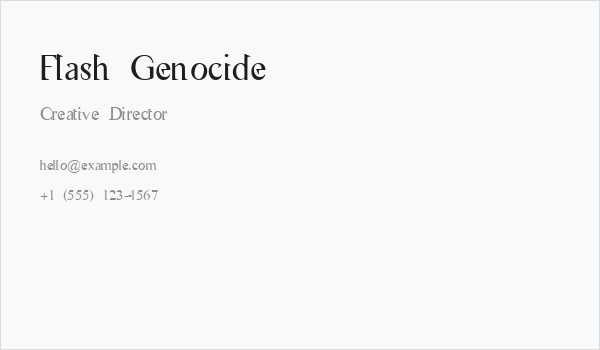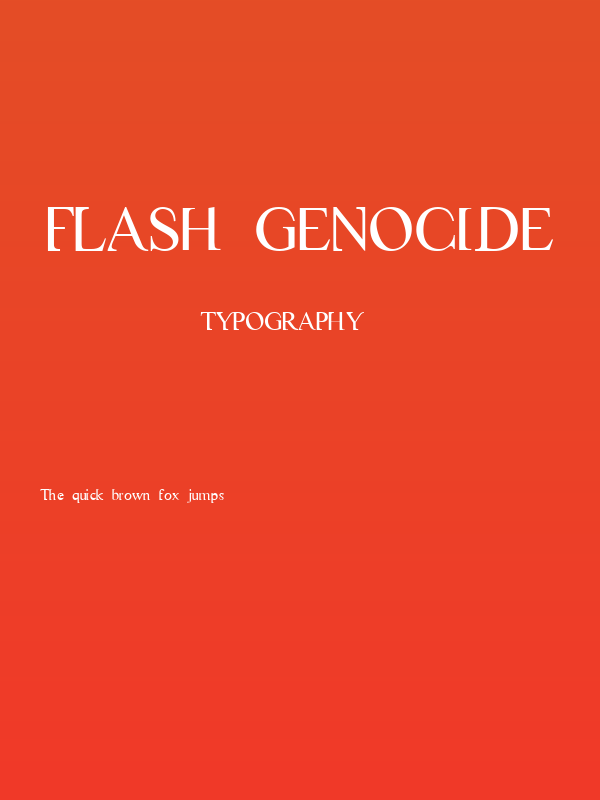
Flash Genocide Font
✎ Serif
| Estilo general | Classic |
| Caso de uso | Headlines, Body text, Logos |
| Proyectos propuestos | This font is perfect for editorial design, book covers, branding projects, and formal invitations. |